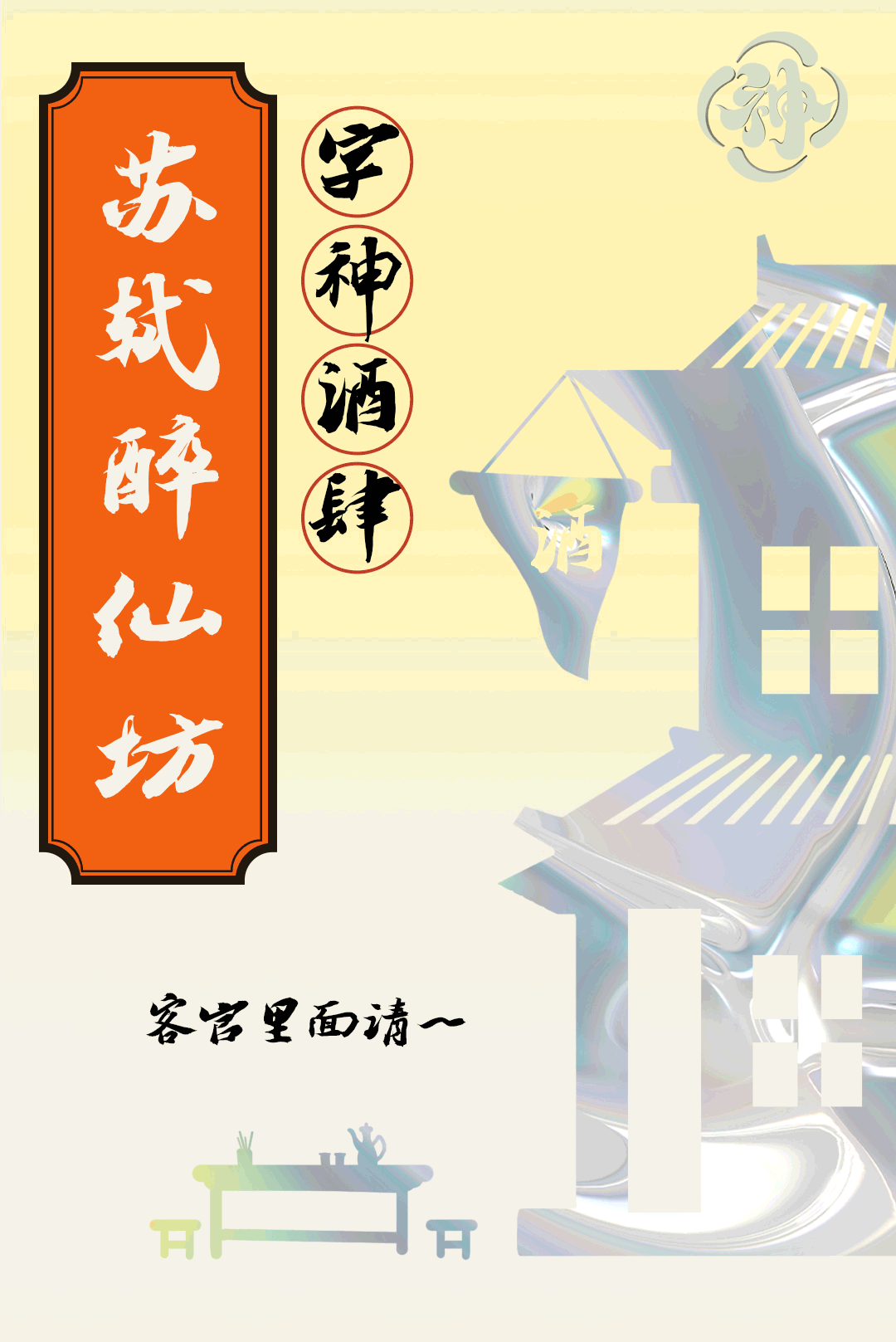
字神苏轼豪放体,感受苏轼书法字体的快意潇洒!
苏轼的酒里,有宋代的雅韵,豪情的旷达,也有千古的愁肠,正如苏轼的字。字神苏轼豪放体,以酒入墨,柔练笔画筋骨,酿造汉字的书香。
字神苏轼豪放体如烈酒,洒脱豪放,妩媚率真,入口柔,回味烈。用笔丰腴,用墨肥润,横画长而有筋骨,竖画厚且重铺毫。字势横向布局,高低错落,轻重起伏,韵律感十足。结体扁平,左右舒展,转折圆润藏锋。
烈酒暖胃,好字流芳。字神苏轼豪放体是以苏轼墨迹字帖为开发依据,进行技术复原的书法字体。字神国风元书院将汉字宝藏以数字化技术保鲜,重塑汉字美感,探寻字体在未来语境的应用边界。